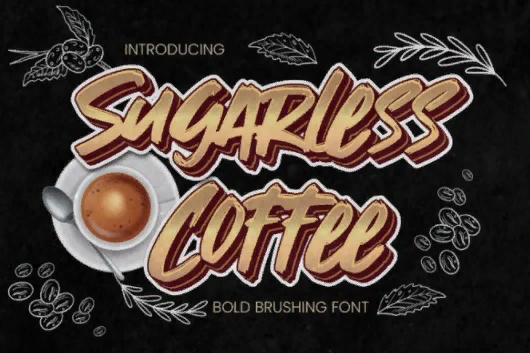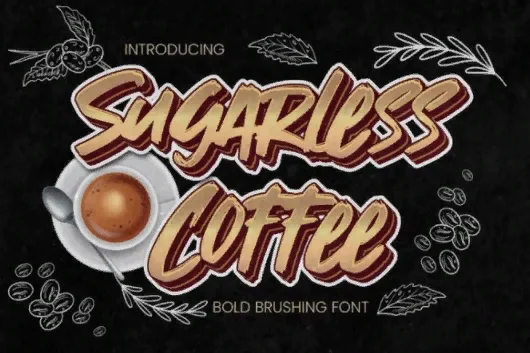
Название: Sugarless Coffee Font (2021)
Привет всем, представляем наш новый продукт Sugarless Coffee - Bold Brushing Font Crafted Display, вдохновленный названием спортивного плаката, и мы делаем его очень энергично.
Шрифт Sugarless Coffee с сильными и вызывающими нюансами. Очень подходит для заголовков, типографики, плакатов, журналов, брошюр, упаковки, веб-сайтов и многого другого для ваших дизайнерских нужд, делая ваши проекты более современными и профессиональными.
Вдохновленный стилем Logo и комбинацией с Cute Craft style. который удовлетворит ваши потребности в дизайне для цитат, спортивной темы, логотипа, словесного знака и т.д. Имеет множество функций opentype и поддерживает несколько языков.